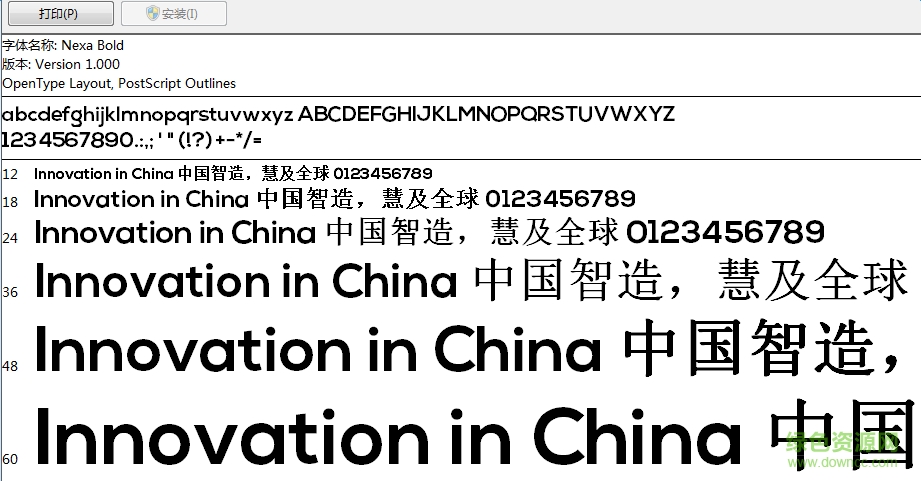
nexabold英文字體
nexabold字體是一款英文字體庫中的個性字體,該字體可以適用于產品包裝、廣告宣傳、出版印刷、商標用字、商業(yè)網站、影視影像視頻、書籍出版印刷等,有需要的朋友可以免費下載收藏。
nexabold字體是一款非常正規(guī)的英文字體,給人一種非常正式的感覺,能夠使用于各類正式場合。有喜歡的朋友趕快來綠色資源網下載使用吧!